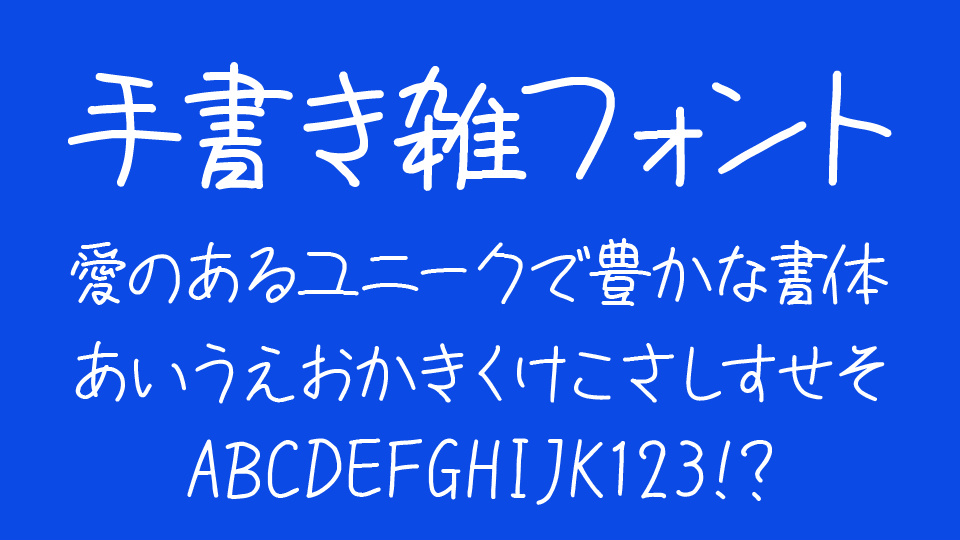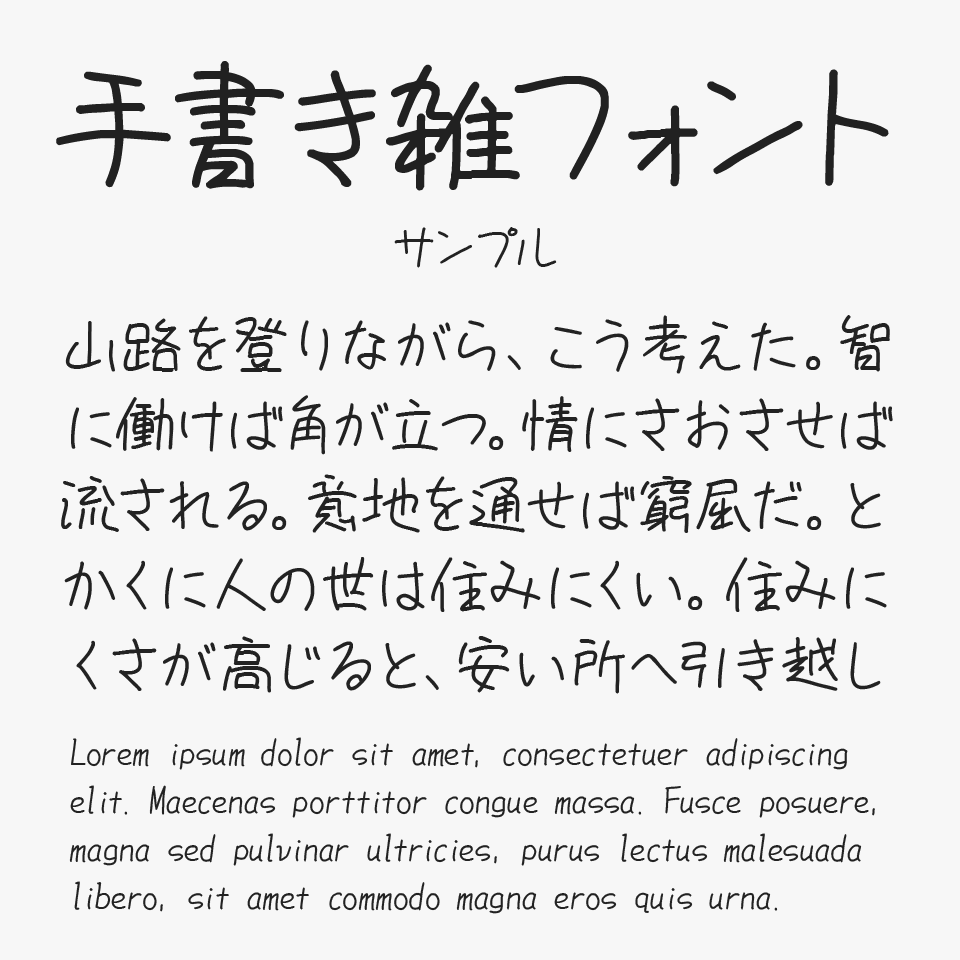
手書き雑フォント
手書き雑フォントは、その名の通り「雑さ」を魅力として制作された手書きフォントです
フォント作者が普段書きやすいと感じる自然な字形をベースに作られており、作り込みすぎていない素朴な表情が特徴となっています。
サササッとメモを書くように書かれた文字には、肩の力が抜けたラフさがあり、気取らない親しみやすさを感じられるフォントです。整いすぎていない文字の揺らぎやバランスが、ほどよいアンニュイ感を生み出しており、見ているだけでもゆるい空気感が伝わってきます。
手書きらしい温かみはありながらも、そこまでかわいらしさを強調しすぎていないため、脱力感のある雰囲気を手軽に取り入れられる、サブカル系デザインや日記風ビジュアル、SNS画像、MV風のタイトルなどにも相性抜群です。
851手書き雑フォント
手書きフォントといえば女性的な可愛らしい手書きフォントが多いですが、こちらは男性的なクセのあるフォントになっております。走り書きのような雑な感じがゆるくて素敵なフォントです。
手書き雑フォントを、ほかのゆるい手書き感を持つフォントと比較してみると、飾らない“雑さ”をそのまま活かした自然体な雰囲気が特に魅力の手書きフォントです。
比較フォントは、「夜すがら手書きフォント」「まきばフォント」「アームドバナナ」「ひょうきんな!?ポップ体」「塩化速記」と使用していますが、どのフォントも独特な脱力感+ゆるさもつ手書きフォントなので、ぜひあわせてチェックしてみてください。
手書き雑フォントと、「夜すがら手書きフォント」「まきばフォント」「アームドバナナ」「ひょうきんな!?ポップ体」「塩化速記」を比較
収録文字は、ひらがな・カタカナ・漢字のJIS第四水準まで・記号・アルファベとを含む34,279字収録されています。